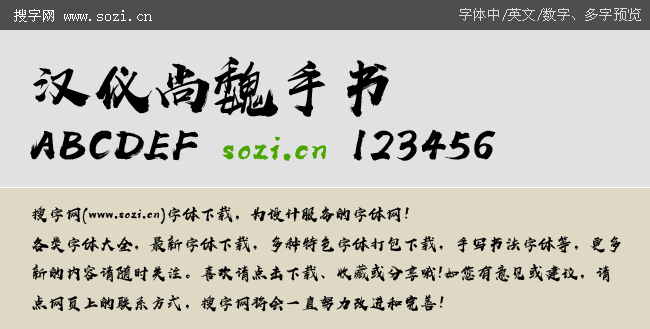
漢儀尚魏手書
搜字網(wǎng)提供一款漢儀尚魏手書中文書法字體下載,漢儀尚魏手書是一款由書法創(chuàng)作人尚巍手寫的書法字體,不管是飛白還是連筆都有著很好的表現(xiàn),邊緣清晰流暢,適合應(yīng)用于廣告設(shè)計、名片設(shè)計、包裝印刷、海報設(shè)計等應(yīng)用。
- 風格類別: 手寫書法體